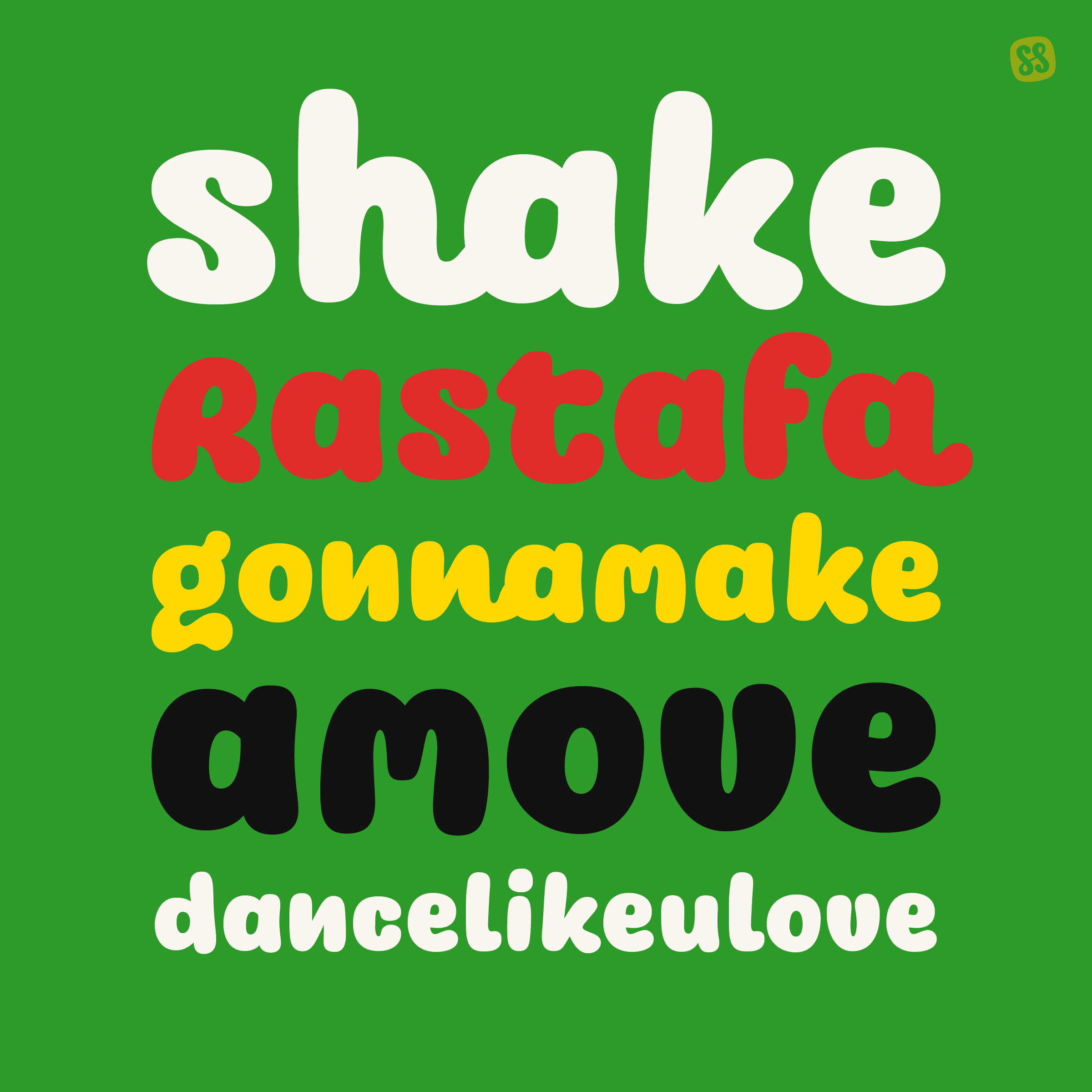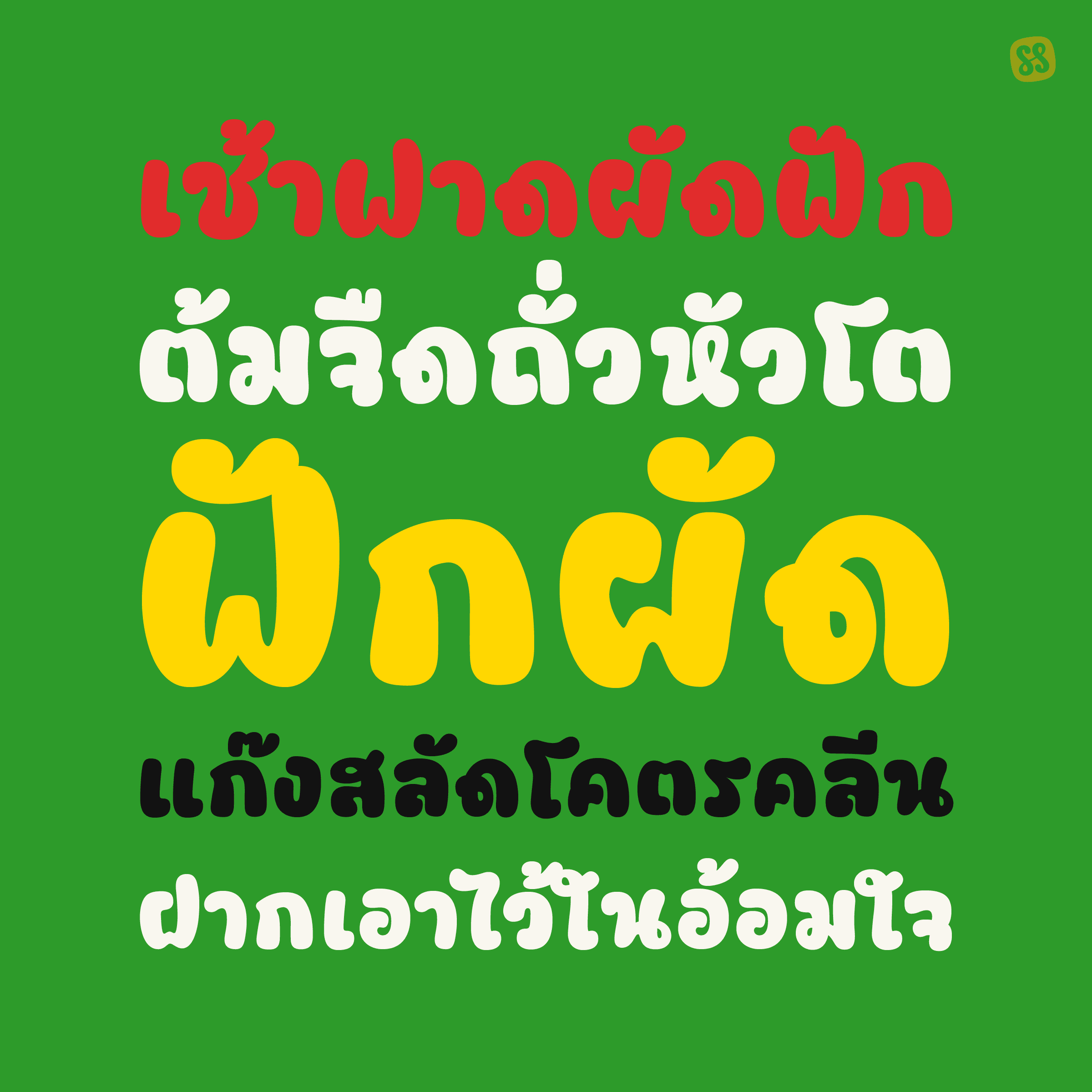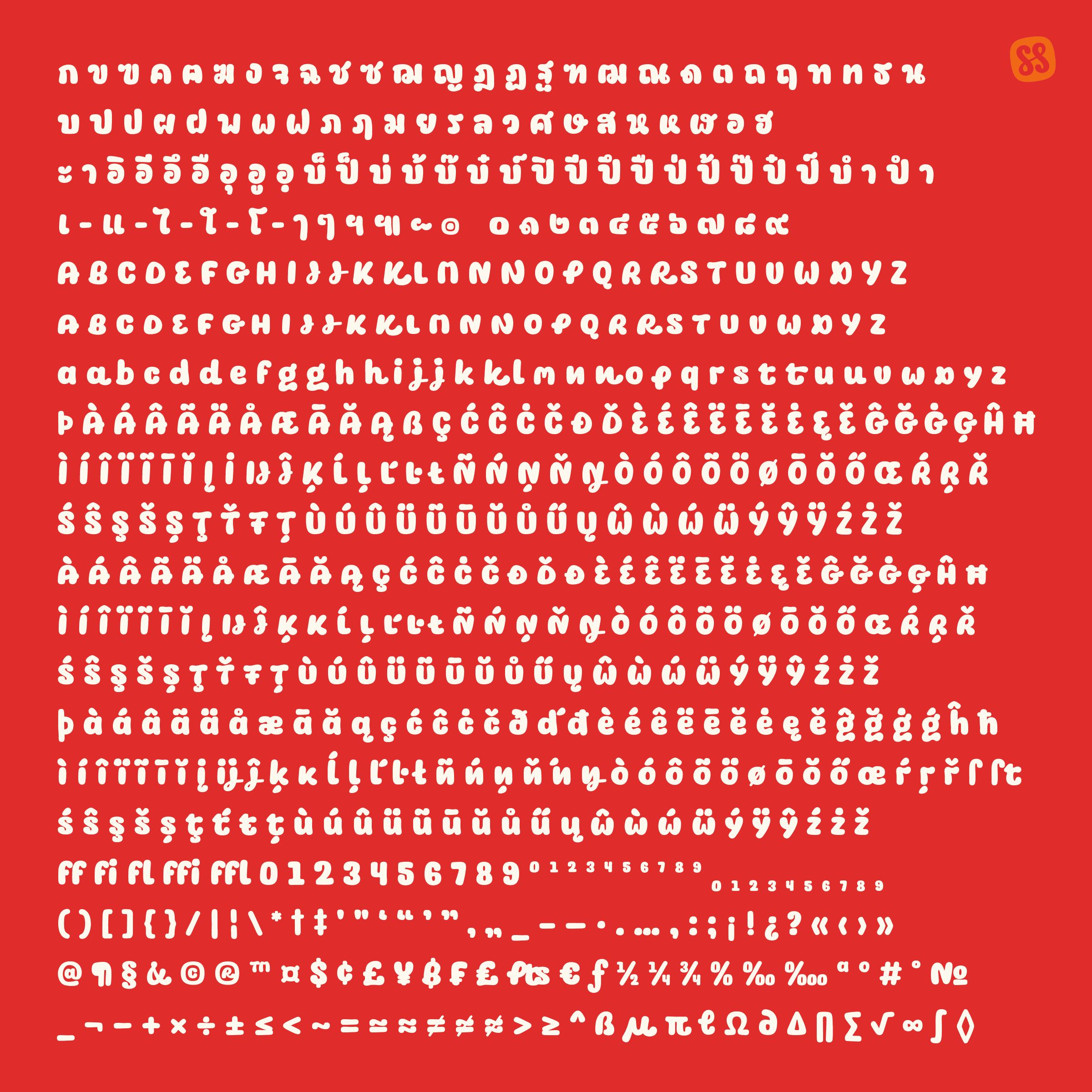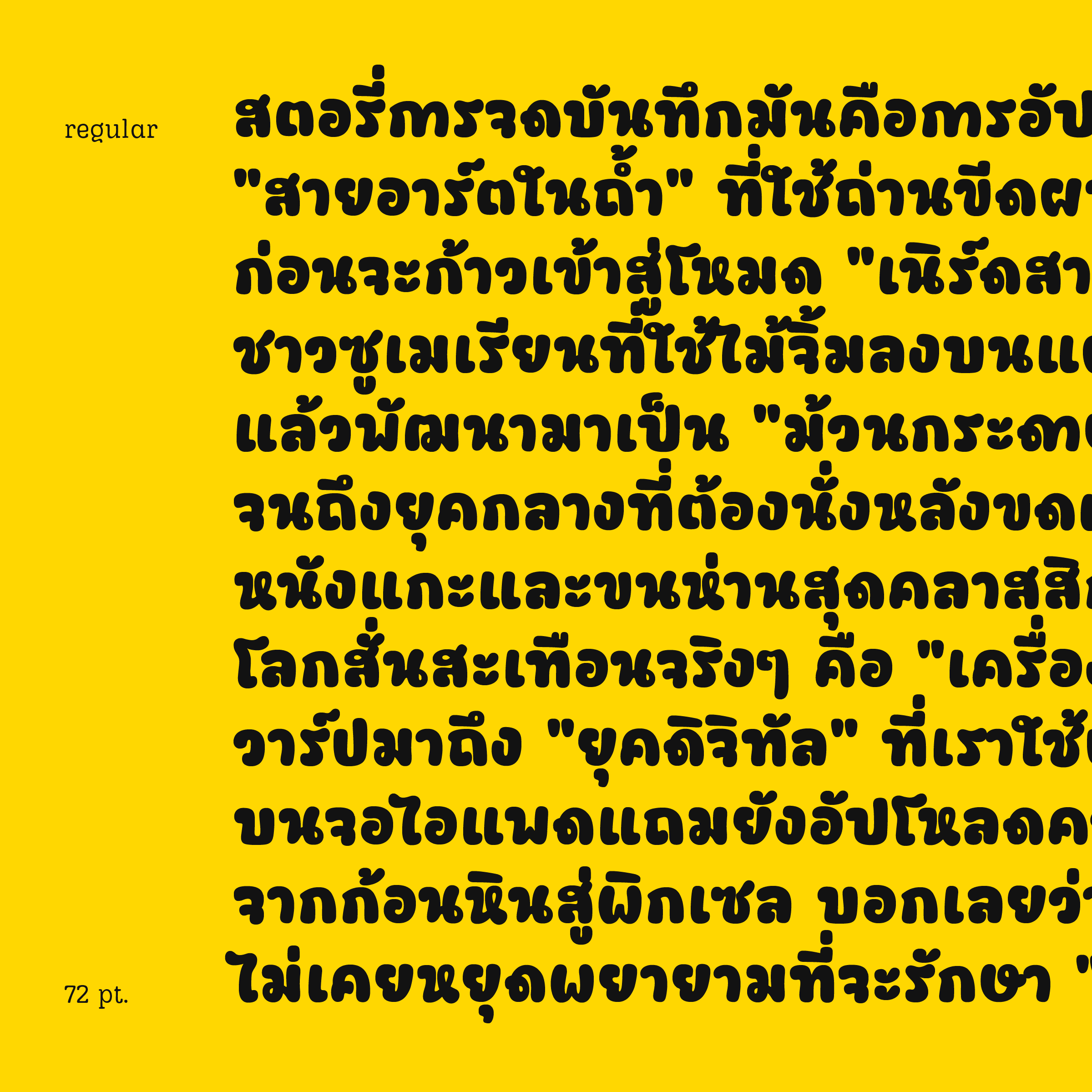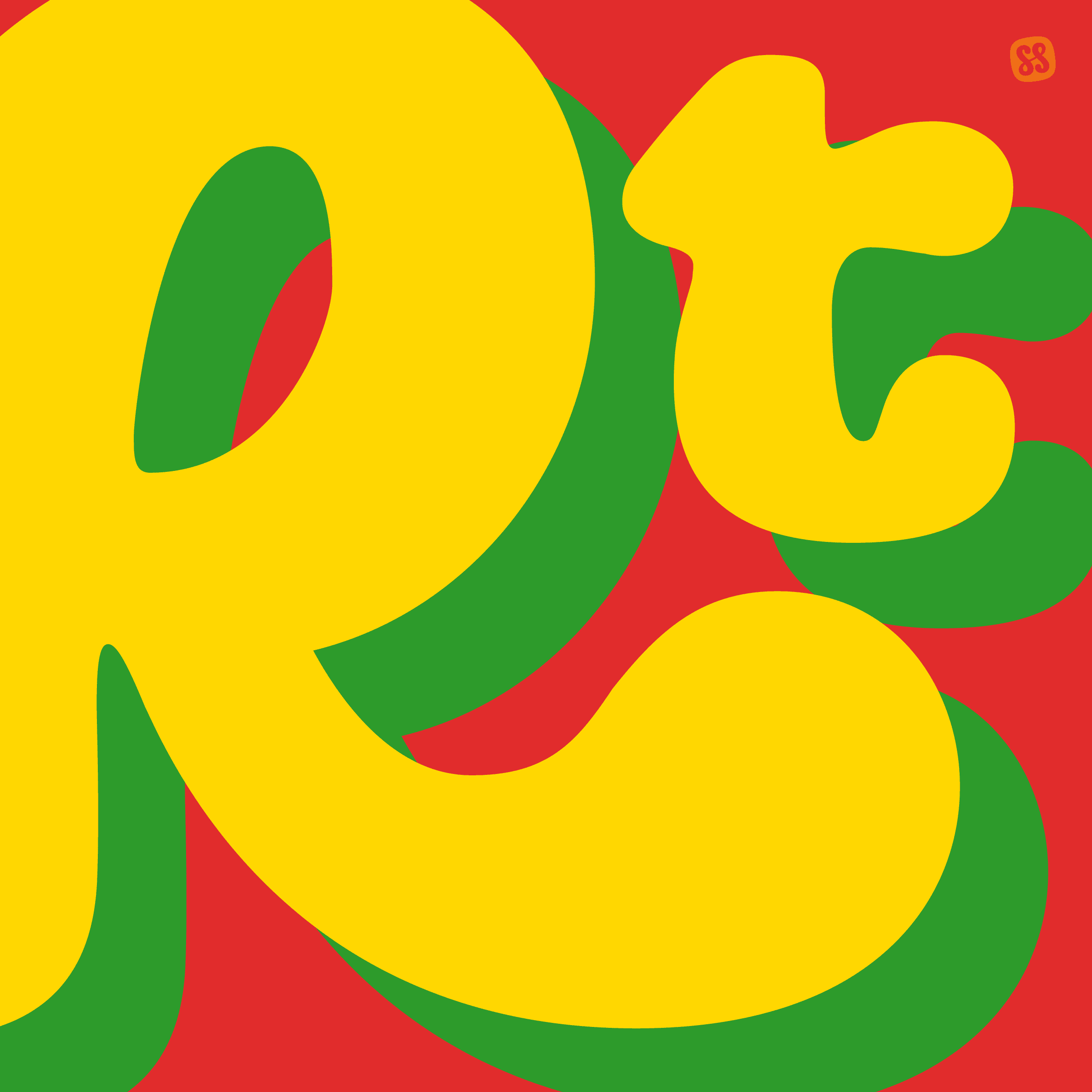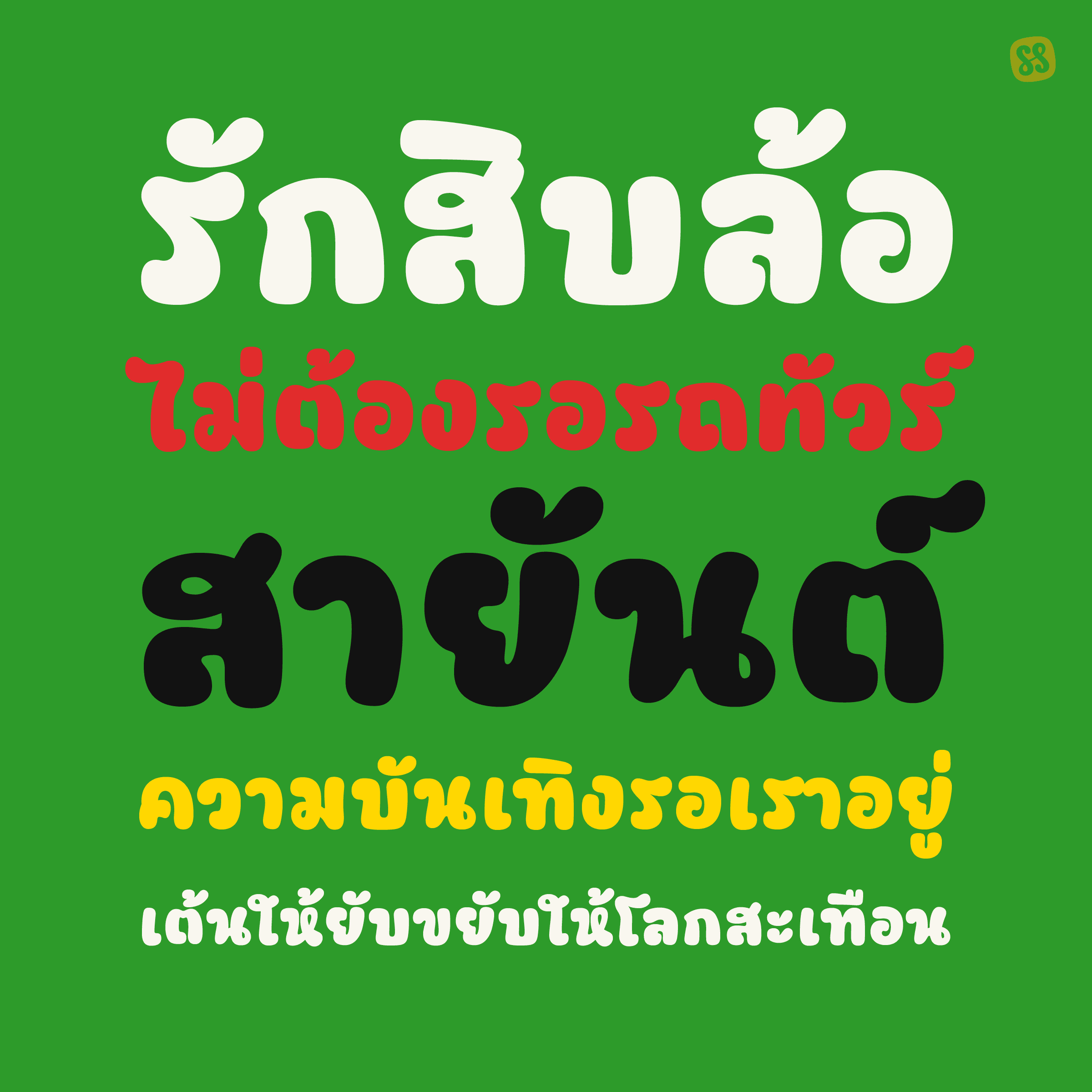
ชื่อฟอนต์ : ถั่ว | TOURR
ถั่ว | TOURR
"ถั่ว | TOURR" คือ ฟอนต์ดิสเพลย์สไตล์ลายมือที่พกพาความสนุกสนานและเป็นกันเองมาแบบเต็มพิกัด ฟอนต์นี้เริ่มต้นจากการสเก็ตช์อย่างอิสระบนหน้ากระดาษ ก่อนจะนำมาวาดเส้นสายใหม่บนคอมพิวเตอร์อย่างพิถีพิถัน ทำให้ได้ตัวอักษรที่มีกลิ่นอายความสนุกแบบงานคราฟต์ แต่ยังคงความเนี้ยบและจัดวางได้สวยงามลงตัว
ด้วยรูปทรงและน้ำหนักตัวอักษรที่ถูกออกแบบมาให้โดดเด่นสะดุดตา "ถั่ว" จึงเหมาะอย่างยิ่งสำหรับการใช้เป็นพาดหัว (Headline) หรือข้อความที่ต้องการพลังงานบวกและการสื่อสารที่เข้าถึงง่าย ไม่ว่าจะเป็นงานกราฟิกสไตล์โจ๊ะ ๆ คอนเทนต์ไวรัล ป้ายสติ๊กเกอร์ฮา ๆ ท้ายรถกระบะ ไปจนถึงงานออกแบบสายชิล ฟอนต์นี้ก็พร้อมจะเข้าไปช่วยเติมชีวิตชีวาและทำให้ข้อความของคุณตะโกนความบันเทิงออกมาได้อย่างมีสไตล์
นอกจากคาแรคเตอร์ที่ชัดเจนและจัดจ้านแล้ว ฟอนต์ "ถั่ว | TOURR" ยังถูกออกแบบมาให้ตอบโจทย์การใช้งานจริงแบบครบเครื่อง โดยมาพร้อมชุดตัวอักษรภาษาไทย ภาษาอังกฤษ ตัวเลข และสัญลักษณ์พิเศษต่าง ๆ แบบจัดเต็ม ไม่ว่าคุณจะหยิบไปจัดวางพาดหัวบนป้ายโฆษณาขนาดใหญ่ พิมพ์สกรีนข้อความกวน ๆ ลงบนเสื้อยืด หรือสร้างสรรค์อาร์ตเวิร์กสำหรับแคมเปญออนไลน์ ฟอนต์ตัวนี้ก็พร้อมมอบจังหวะสนุก ๆ สไตล์เรกเก้ที่ผสมผสานเข้ากับความเก๋าแบบสิบล้อคลาสสิกได้อย่างลงตัว ช่วยให้ทุกผลงานของคุณดูมีอารมณ์ขัน โดดเด่นจดจำง่าย และยังคงมาตรฐานความประณีตในทุกการจัดวางตามแบบฉบับของธรรมดาสตูดิโอเช่นเคย
ชุดฟอนต์ "ถั่ว"
ประกอบด้วยฟอนต์ 1 น้ำหนัก 1 ฟอนต์
• TOURR Regular
ออกแบบโดย : Montonn Thanaroj